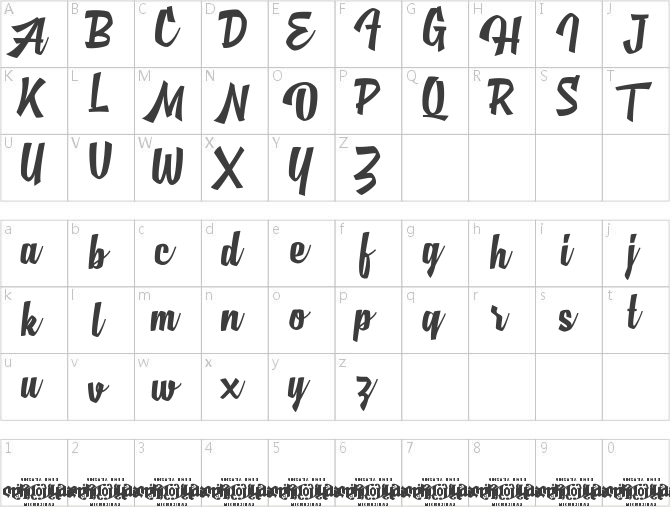
MJ AlGhifari Demo
MJ AlGhifari Demo介紹
MJ AlGhifari Demo字體字庫是一款讓人賞心悅目、百看不厭的英文字體,適合各類廣告和產品包裝設計應用,字體大小0.25MB,格式為ttf字體,上傳用戶是afig,作者/版權方為未知
MJ AlGhifari Demo效果圖